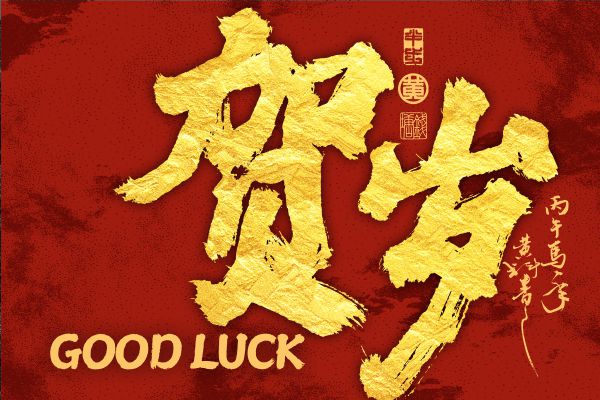
汉仪黄科榜书 W
汉仪黄科榜书 W 是汉仪字库推出的一款兼具中国风与力量感的手写体字体,以雄浑豪放的笔势与古典韵味的设计,成为传递传统文化精神与现代设计需求的优质选择。 从字形结构来看,汉仪黄科榜书 W 字形方正稳健,重心居中且中宫宽博,既保留了传统榜书的大气格局,又通过方头笔画与断开的笔锋设计,打破平正求稳的传统框架,展现出独特的视觉张力。字体笔画粗壮饱满,粗细均匀的线条中,起笔与收笔处的明显顿笔装饰更添力量感,方头笔画利落干脆,既彰显手写书法的洒脱随性,又传递出豪放不羁的气势,完美契合“力量”“古典”“手写风”的风格定位。 区别于传统榜书的平稳,汉仪黄科榜书 W 大胆追求力量的释放与章法的灵动,凝练洒脱的笔触让字体兼具强烈的视觉冲击力与现代设计感。无论是古典文化主题设计、品牌标识塑造,还是需要传递力量与个性的宣传场景,汉仪黄科榜书 W 都能以其独特的手写韵味与文化底蕴,为作品注入鲜活的生命力。
黄科
黄科(笔名:半步)当代青年书法家,师从著名书法家,诗词楹联学家,剧作家钱法成先生学习传统书法。从事当代书法艺术创作与视觉融合性实践,商业书法应用实践与理论研究。